28 Font Graffiti Terbaik Untuk Desain Perkotaan
Diterbitkan: 2022-04-18Font grafiti ideal untuk seni jalanan, stiker, dan desain lain yang Anda coba ciptakan estetika perkotaan eklektik. Mereka kuat, tegang, dan penuh kepribadian.
Untuk membantu Anda menemukan jenis huruf yang sempurna untuk proyek desain gaya jalanan Anda, kami telah menyusun daftar font grafiti terbaik di pasar.
Kami memilih daftar ini dan memastikan untuk hanya menyertakan tipografi terbaik dari desainer terbaik. Ada campuran opsi gratis dan premium, jadi Anda harus dapat menemukan sesuatu yang sesuai dengan proyek dan anggaran Anda.
Apa itu Font Graffiti?
Font grafiti adalah tipografi yang terinspirasi oleh seni jalanan. Mereka kurang ajar, keras, dan berkarakter, dan biasanya terlihat seolah-olah mereka telah digores, dicoret, atau disemprotkan ke permukaan.
Ada banyak jenis font grafiti, tetapi beberapa yang paling populer meliputi:
- Font stensil . Ini mencoba untuk menciptakan kembali tampilan yang akan Anda dapatkan dengan menyemprotkan lukisan grafiti di atas stensil. Pikirkan Banksy.
- Font lempar. Ini adalah font seperti tag yang biasanya terdiri dari huruf gelembung.
- Font gaya liar . Wildstyle adalah gaya grafiti yang rumit dan rumit. Jenis font ini cenderung sulit dibaca dan sangat bergaya.
- Font menetes . Gaya font grafiti ini memiliki bentuk huruf yang terlihat seperti cat yang menetes.
- Font kuas . Ini adalah tipografi yang mencoba meniru sapuan kuas
- Font coretan . Jenis font grafiti ini terlihat seperti ditulis tangan secara kasar dan sembarangan dengan pena atau pensil, seperti yang mungkin Anda corat-coret di buku catatan.
Tidak seperti jenis font lainnya, font Graffiti tidak dirancang dengan mempertimbangkan keterbacaan. Mereka murni artistik. Dengan demikian, mereka biasanya bukan pilihan yang baik untuk hal-hal seperti judul atau teks isi, tetapi mereka sangat artistik dan dapat terlihat bagus di poster, produk fesyen, dan stiker.
28 Font Graffiti Terbaik
1. Nasib Malam – Pilihan Utama Kami
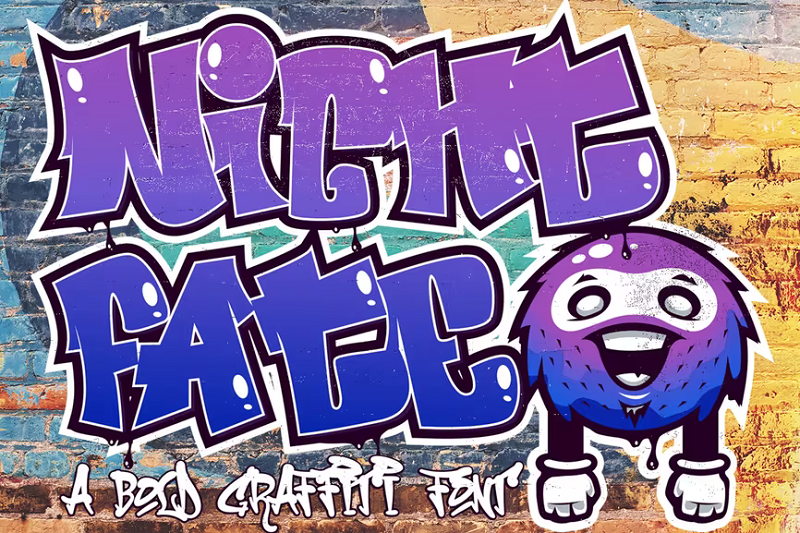
Nightfate, menurut figuree, adalah font grafiti paling populer di Envato Elements — dan saya dapat melihat alasannya. Ini menggunakan karakter tebal seperti gelembung dengan campuran tepi membulat dan sudut tajam dan hadir dalam format TTF, OTF, dan WOFF.
Mengapa ini pilihan utama kami?
Nightfate memiliki semua yang kami cari dalam font grafiti. Ini menggunakan desain gaya klasik throw-up yang harus akrab bagi siapa saja yang pernah tinggal di daerah perkotaan. Ini adalah skrip serbaguna yang tidak akan terlihat tidak pada tempatnya di mural seni jalanan tetapi juga akan bekerja dengan baik dalam desain pakaian, dekorasi dinding dan stiker, dan bahkan logo.
2. Berguling
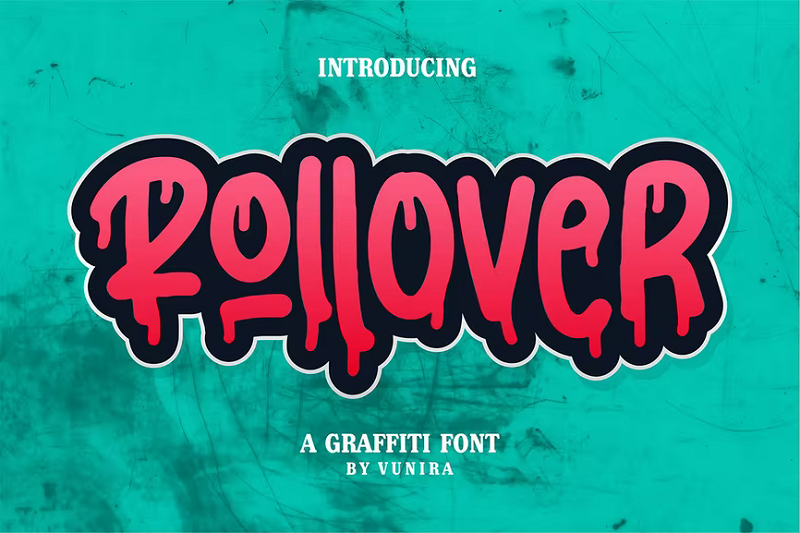
Rollover adalah font grafiti obat bius oleh Vunira. Efek tetesan membuat bentuk huruf terlihat seperti telah disemprot dan catnya masih basah. Itu juga menjadikan ini font yang bagus untuk desain bertema horor karena dalam warna yang tepat, efek menetes dapat mengingatkan kita pada darah. Ini mungkin bekerja dengan baik pada sampul buku horor, stiker, dan poster film. Paket font juga dilengkapi dengan alternatif gaya, pengikat, dan sapuan.
3. Font Melempar
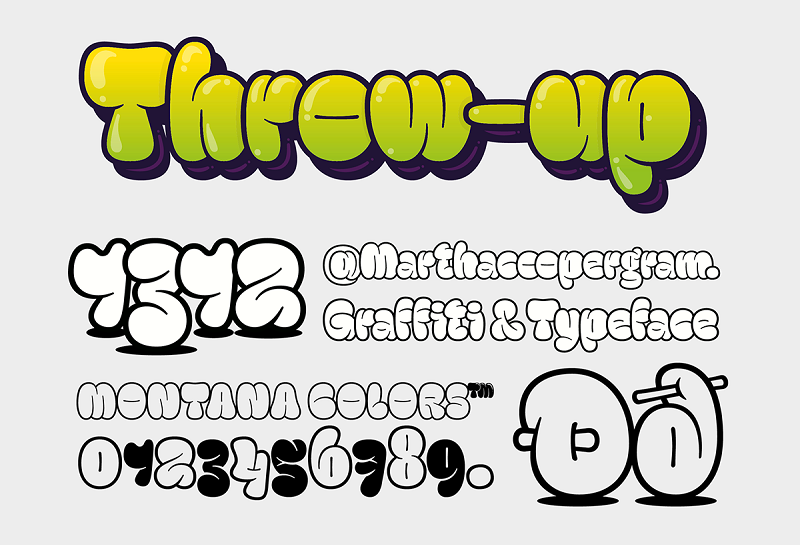
Ini adalah font lemparan berlapis yang keren oleh desainer Gasper Munoz. Perancangnya (yang berlatar belakang grafiti) mengambil inspirasi dari budaya grafiti, khususnya “bom” dan “jepit”, subtipe grafiti yang dapat dibuat dengan cepat dan dikenal dengan bentuknya yang sederhana.
Jepit dan bom biasanya dibuat dengan cat semprot dan katup yang memungkinkan transisi cat antara goresan tipis dan tebal, dan Gasper telah mencoba menangkap ini dalam jenis hurufnya. Tidakkah Anda menyukai bentuk huruf bulat yang lucu itu?
Paket font hadir dengan empat versi: stroke, fill, shadow, dan highlight. Variasi yang berbeda ini dapat berlapis satu sama lain untuk menciptakan desain yang menarik perhatian yang tampak seperti melompat dari halaman.
4. Hayword
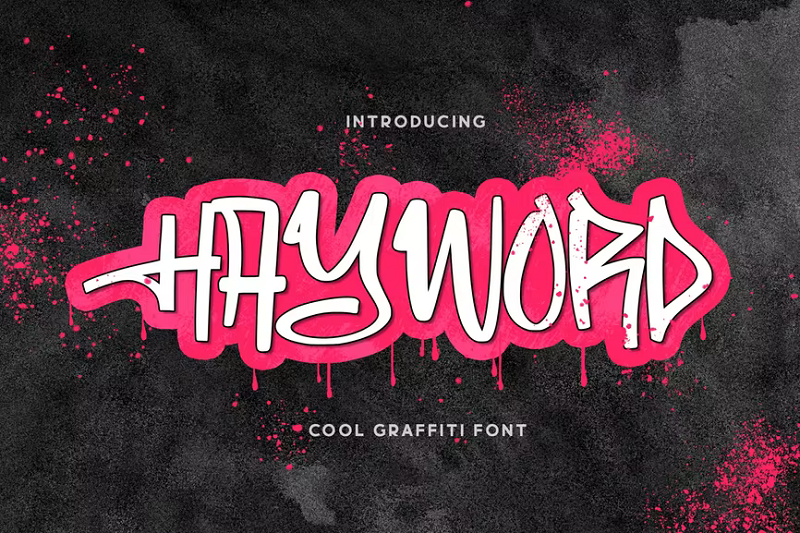
Hayword adalah gaya grafiti keren lainnya oleh desainer garisman. Ini terinspirasi oleh seni jalanan dan mengingatkan saya pada jenis label yang mungkin Anda lihat di dinding bata. Ini akan bekerja dengan baik pada desain hip-hop, pakaian streetwear, dan seni dinding. Muncul dengan huruf besar, tanda baca, dan angka dalam format OTF dan TTF.
5. Luser
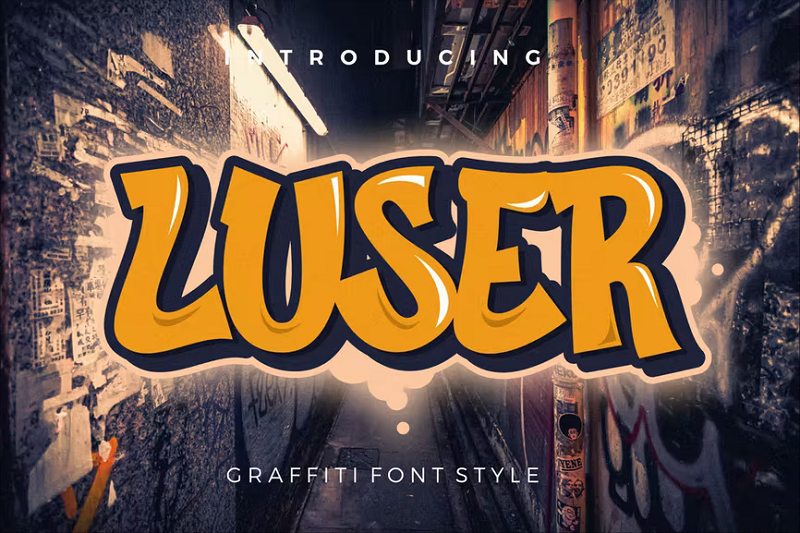
Luser adalah font seni jalanan modern yang terinspirasi oleh budaya hip-hop dan grafiti. Ini fitur sapuan kuas halus yang terlihat obat bius dan itu salah satu font grafiti lebih mudah dibaca dalam daftar ini sehingga dapat bekerja dengan baik di berita utama.
Harga: Penggunaan pribadi dan komersial termasuk dalam langganan Envato Elements ($16,50/bulan)
6. Bombsky
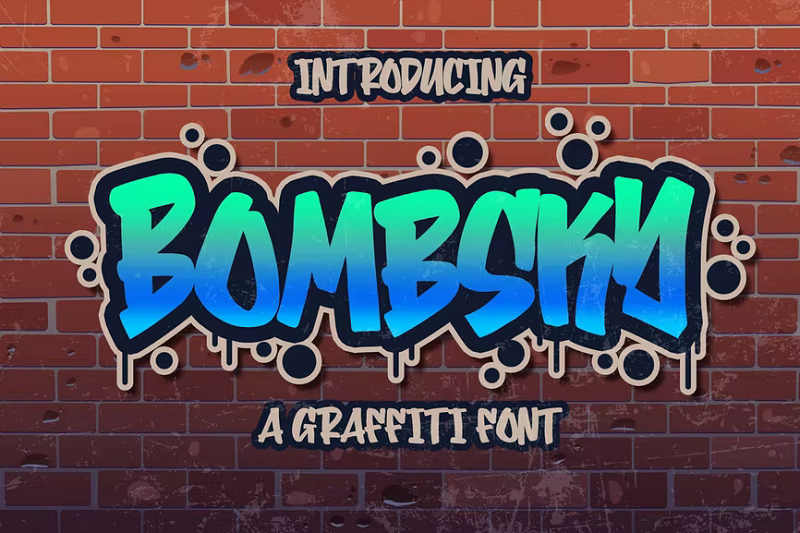
Lupakan Banksy, izinkan saya memperkenalkan Anda pada Bombsky—font grafiti dari Blankids. Seperti namanya, desainnya didasarkan pada bom grafiti klasik (pengingat: bom adalah tag grafiti sederhana yang dapat dilempar dengan cepat). Saya dapat melihat ini terlihat sangat bagus di sampul album hip-hop.
Harga: Penggunaan pribadi dan komersial termasuk dalam langganan Envato Elements ($16,50/bulan)
7. Anak Punk
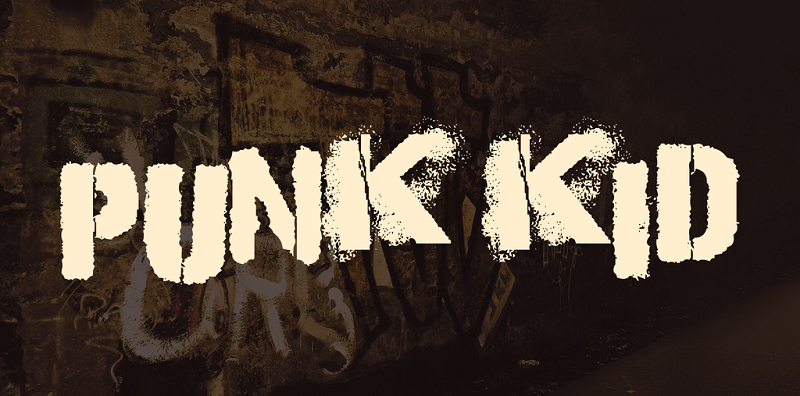
Lepaskan punk batin Anda dengan font stensil bergaya grafiti gratis ini oleh Chris Hansen. Punk Kid tidak seperti font lain yang telah kita lihat sejauh ini karena menggunakan gaya stensil klasik, dengan bentuk huruf yang rapi dan seragam. Seperti huruf stensil, ada jeda di wajah setiap mesin terbang.
Apa yang membuat Punk Kid berbeda dari font stensil klasik, adalah tekstur terkikis yang keren dan efek berbintik-bintik, yang keduanya membuatnya terlihat seperti disemprotkan dengan terburu-buru. Ini adalah font yang sangat pemberontak yang akan terlihat bagus pada desain dendam, situs band, sampul album, poster konser, dan banyak lagi.
Font ini dengan murah hati telah tersedia secara gratis, bahkan untuk penggunaan komersial. Tetapi jika Anda ingin menunjukkan rasa terima kasih Anda, perancang mendorong Anda untuk menyumbang ke rumah sakit koala di NSW.
Harga: Gratis
8. Beslyn
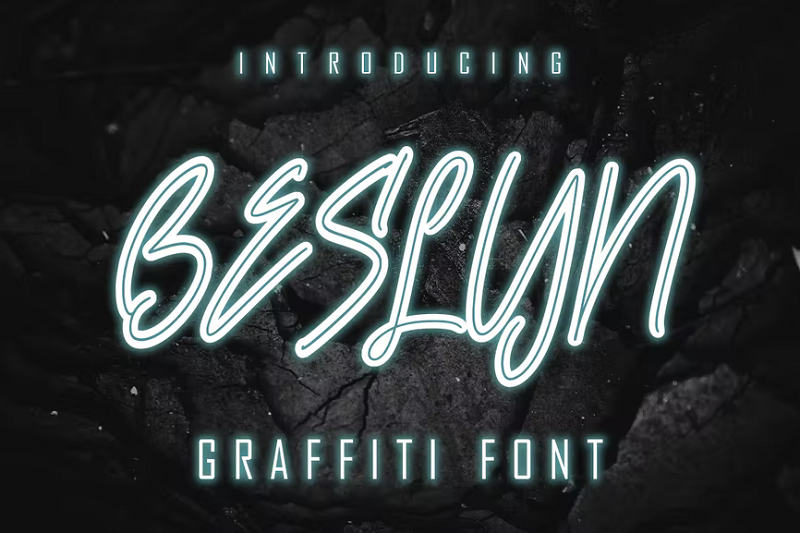
Beslyn adalah font tipe grafiti yang ramping dan canggih oleh Skiiler Studio. Gaya elegan cocok untuk desain yang lebih serius, profesional, atau bergaya dan terlihat sangat bagus saat dipasangkan dengan latar belakang yang lebih gelap. Ini adalah jenis huruf sebaris, yang berarti memiliki garis tipis garis rambut di setiap bentuk huruf untuk menambah kontras dan minat visual.
Harga: Penggunaan pribadi dan komersial termasuk dalam langganan Envato Elements ($16,50/bulan)
9. Rumah Sakit
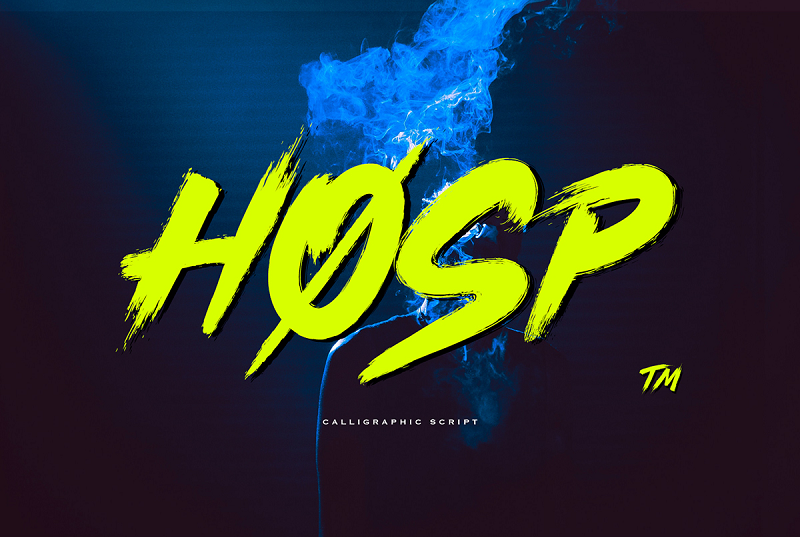
Hosp adalah skrip kaligrafi edgy oleh Nick Asphodel Design. Perancang ingin 'membantu orang-orang artistik untuk membuat desain yang spektakuler' dan membuat Hosp dengan tangan menggunakan kuas runcing. Bentuk huruf miring, bintik tinta, dan sapuan kuas yang kasar terlihat membosankan dan menciptakan suasana yang kuat. Yang ini cocok untuk desain produk edgy, cap print, stiker, dan desain urban lainnya.
Harga: Gratis
10. Airneo
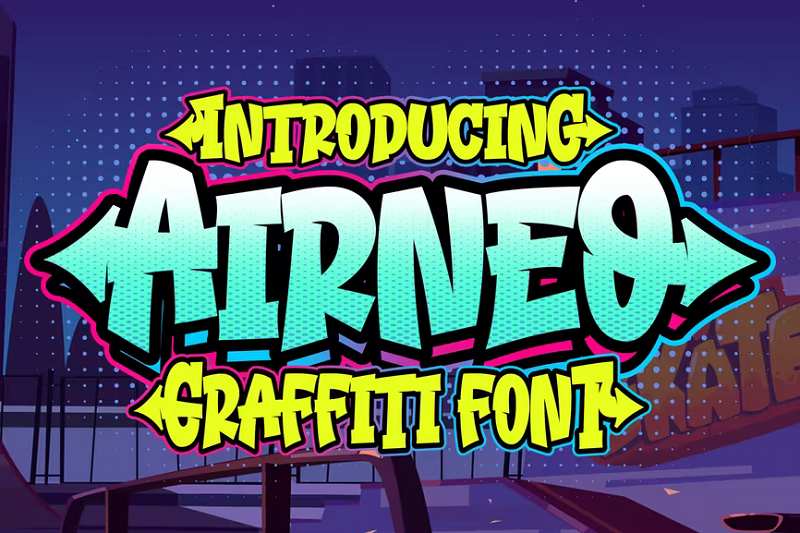
Airneo adalah font grafiti mengagumkan lainnya yang membuat saya berpikir tentang lapangan basket, sepatu kets, dan hip hop. Ini menggunakan desain yang menyenangkan, menarik, dan berani, dengan hiasan menarik seperti panah di ujung palang untuk menambah bakat. Ini fitur huruf besar dan kecil, angka, tanda baca, dan mesin terbang multibahasa.
Harga: Penggunaan pribadi dan komersial termasuk dalam langganan Envato Elements ($16,50/bulan)
11. Pikirkan Kesenjangannya
Mind the Gap adalah font stensil lain yang dapat bekerja dengan baik dalam seni jalanan dan desain yang terinspirasi grafiti. Perancang terinspirasi oleh hubungan cinta/benci yang dia miliki dengan perjalanan sehari-harinya di London (oleh karena itu namanya, yang seharusnya tidak asing bagi siapa saja yang pernah bepergian dengan kereta bawah tanah).
Font mencerminkan sifat industri, utilitarian dari stasiun bawah tanah di kota-kota besar. Itu dibuat dengan stensil huruf potong tangan dan cat semprot di atasnya. Tampilan militer diimbangi oleh ketidaksempurnaan yang disengaja yang membuatnya terlihat hampir kotor dan menyuntikkan beberapa kepribadian ke dalam apa yang seharusnya menjadi desain yang relatif membosankan.
Harga: Penggunaan pribadi dan komersial termasuk dalam langganan Envato Elements ($16,50/bulan)
12. Kemarahan Jalan
Road Rage adalah font grafiti agresif oleh Youssef Habchi. Sudut tajam dan sapuan kuas bertekstur menambah dampak dan menjadikannya salah satu font yang paling menarik dalam daftar ini. Aku mulai marah hanya dengan melihatnya.
Harga: Gratis
13. Bradwall
Selanjutnya, kita memiliki font grafiti Bradwall oleh Blankids. Tidakkah menurut Anda ini akan terlihat konyol di atas skateboard? Sekali lagi, ia menggunakan gaya lemparan yang sudah dikenal dengan bentuk huruf gelembung bulat. Itu datang dalam dua gaya: reguler dan garis besar.
Harga: Penggunaan pribadi dan komersial termasuk dalam langganan Envato Elements ($16,50/bulan)
14. Kegilaan
Insanity adalah font tipe grafiti modern dengan gaya uniknya sendiri, dari studio TKK. Perancang telah memilih goresan yang lebih tipis daripada huruf gelembung yang sering Anda temukan dalam font gaya lempar, yang membuat yang ini sedikit lebih fleksibel. Ini kacau, liar, dan gangster hella. Cobalah di poster, majalah jalanan, sampul YouTube, gambar mini, dan pos sosial Anda.
Harga: Penggunaan pribadi dan komersial termasuk dalam langganan Envato Elements ($16,50/bulan)
15. Diediedie Font
Selanjutnya, kami memiliki sesuatu yang sedikit berbeda. Diediedie adalah 'font coretan jahat yang tidak boleh dipercaya'. Alih-alih sapuan kuas atau cat semprot, itu meniru jenis coretan maniak, coretan yang mungkin dilakukan dengan pena di buku catatan.
Ini menakutkan dan sedikit kejam, yang menjadikannya font yang sempurna untuk desain horor dan sampul album musik rock. Selain semua mesin terbang biasa, perancang juga menyertakan beberapa dingbat yang bagus (seperti pentagram dan tengkorak) yang dapat Anda gunakan untuk menghidupkan desain Anda.
Harga: Gratis
16. Kepala ular
Snakehead adalah font skrip seperti tag yang akan terlihat bagus di logo, streetwear, branding, dan desain lainnya. Ini adalah font huruf besar semua yang dilengkapi dengan huruf AZ, angka, dan tanda baca, serta berbagai alternatif dan tanda kutip.
Harga: Penggunaan pribadi dan komersial termasuk dalam langganan Envato Elements ($16,50/bulan)
17. Flim Flom
Warnai desain Anda dengan estetika buatan tangan dengan Flim Flom oleh Maulana Creative. Ini adalah jenis huruf yang sangat dekoratif yang terlihat seperti digambar dengan spidol atau spidol. Sentuhan kecil seperti mengganti judul pada huruf seperti i dan j dengan tanda silang menambah daya tarik visual dan menjadikan ini salah satu font paling orisinal dalam daftar ini.
Harga: Penggunaan pribadi dan komersial termasuk dalam langganan Envato Elements ($16,50/bulan)
18. Font Degrassi
Degrassi adalah font aneh yang terinspirasi dari grafiti yang menampilkan garis bergelombang dan goresan yang diakhiri dengan panah. Ini tersedia secara gratis dan akan bekerja dengan baik dalam grafik game, kaos, logo, poster, dan banyak lagi.
Harga: Gratis
19. MWD Graff
MWD Graff adalah font grafiti gaya liar oleh Priority Type Co. Dalam gaya gaya liar sejati, font ini menampilkan goresan yang rumit dan sangat detail. Ini bukan font yang paling mudah dibaca dalam daftar ini, tetapi sangat artistik. Muncul dalam dua gaya: dasar dan mengusir. Anda dapat menambahkan versi ekstrusi di belakang versi reguler sebagai lapisan untuk membuat efek 3D.
Harga: Penggunaan pribadi dan komersial termasuk dalam langganan Envato Elements ($16,50/bulan)
20. Mengisi Urban
Fillings Urban adalah font gaya grafiti chunky yang terinspirasi oleh budaya anak muda. Ini ditandai dengan bentuk huruf montok, goresan tebal, dan penghitung yang terlihat seperti salib. Ini terlihat samar-samar kartun dan dapat bekerja dengan baik dalam komik dan kartun serta desain perkotaan yang terinspirasi jalan.
Harga: Penggunaan pribadi dan komersial termasuk dalam langganan Envato Elements ($16,50/bulan)
21. Font Graffiti
'font grafiti' yang diberi nama tepat oleh Mike Karolos menyenangkan dan menyenangkan. Ini tidak terlihat agresif seperti beberapa font lain dalam daftar ini dan mungkin berfungsi dengan baik dalam desain ramah anak seperti sampul buku anak-anak, game seluler, dan kemasan produk mainan.
Harga: Gratis
22. Jalan Perkotaan
Street Urban adalah font lain yang terinspirasi dari grafiti yang menyenangkan dan berani. Ini terlihat bagus dalam warna-warna cerah dan seperti font terakhir akan sempurna untuk desain ramah anak seperti poster anak-anak dan sampul buku.
Harga: Penggunaan pribadi dan komersial termasuk dalam langganan Envato Elements ($16,50/bulan)
23. Membungkuk
Bowings adalah font grafiti yang tinggi dan berani dengan tema yang menyenangkan. Ini bagus untuk kartun, komik, stiker, dan seni dinding.
Harga: Penggunaan pribadi dan komersial termasuk dalam langganan Envato Elements ($16,50/bulan)
24. Autobahn
Autobahn (bahasa Jerman untuk jalan tol) adalah jenis huruf stensil lain dengan banyak detail. Ini sangat mirip dengan Mind The Gap, tetapi dengan beberapa sentuhan yang memberikan bakat uniknya sendiri. Ini bukan font vektor tradisional dan malah menggunakan format OpenType SVG yang baru, itulah sebabnya font ini sangat realistis dan detail.
Harga: Penggunaan pribadi dan komersial termasuk dalam langganan Envato Elements ($16,50/bulan)
25. Bagian Depan Grafiti Gratis
Jika Anda mencari font grafiti unik yang dapat Anda gunakan secara gratis, ini dia. Ini memiliki desain yang terinspirasi Wildstyle dengan huruf bergelombang yang sulit dibaca, sehingga tidak akan berfungsi dengan baik dalam teks isi tetapi sangat cocok untuk tampilan.
Harga: Gratis
26. Nezuko
Nezuko adalah font unik dengan sudut tajam dan tidak ada kurva sama sekali. Ini bukan font grafiti tradisional tetapi menggabungkan beberapa elemen yang menjadi ciri khas gaya. Ini sangat estetis dan mungkin terlihat sangat bagus dalam judul game indie, sampul buku, dan poster film.
Harga: Penggunaan pribadi dan komersial termasuk dalam langganan Envato Elements ($16,50/bulan)
27. Kadal Kotor
Dirty Lizard adalah font grafiti gaya tag lain yang akan menjadi tambahan yang bagus untuk berbagai proyek desain. Itu bisa bekerja pada segala hal mulai dari logo dan label hingga desain dan judul pakaian.
Harga: Penggunaan pribadi dan komersial termasuk dalam langganan Envato Elements ($16,50/bulan)
28. Pelukis Dinding
Last but not least, kami memiliki Wall Painter — font kuas kasar dari Tokopress. Tidak seperti kebanyakan font grafiti lainnya, font ini tidak memiliki efek cat semprot. Sepertinya sang desainer melukis dengan sapuan kuas lebar. Ini ideal untuk desain pemberontak seperti spanduk protes, poster musik, posting media sosial yang tegang, dan majalah musik.
Harga: Penggunaan pribadi dan komersial termasuk dalam langganan Envato Elements ($16,50/bulan)
Cara Memilih Font Graffiti
Seperti yang Anda lihat, ada banyak font grafiti di luar sana untuk dipilih — jadi bagaimana Anda memilih yang tepat untuk proyek Anda ? Nah, berikut adalah beberapa faktor yang perlu dipertimbangkan saat menimbang pilihan Anda:
- Gaya. Font grafiti datang dalam berbagai bentuk dan gaya, seperti wildstyle, throw-up, stensil, dll. Cobalah untuk memilih salah satu yang sesuai dengan estetika karya seni atau proyek desain Anda.